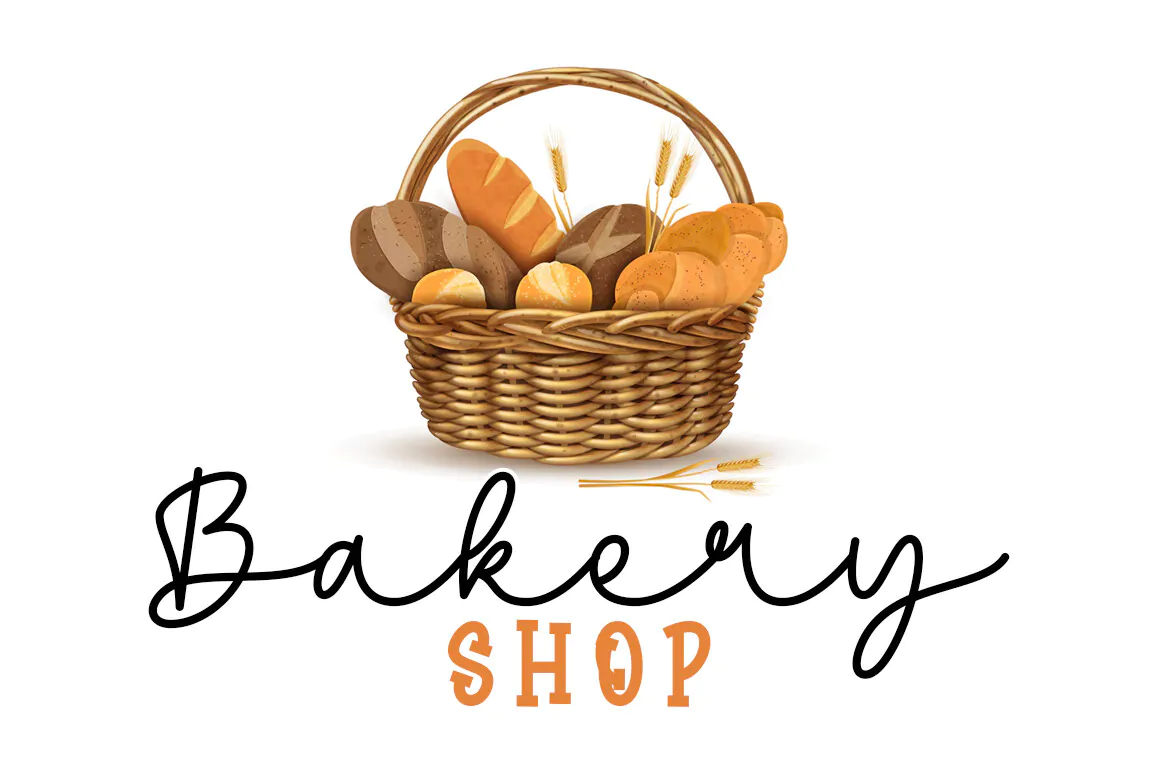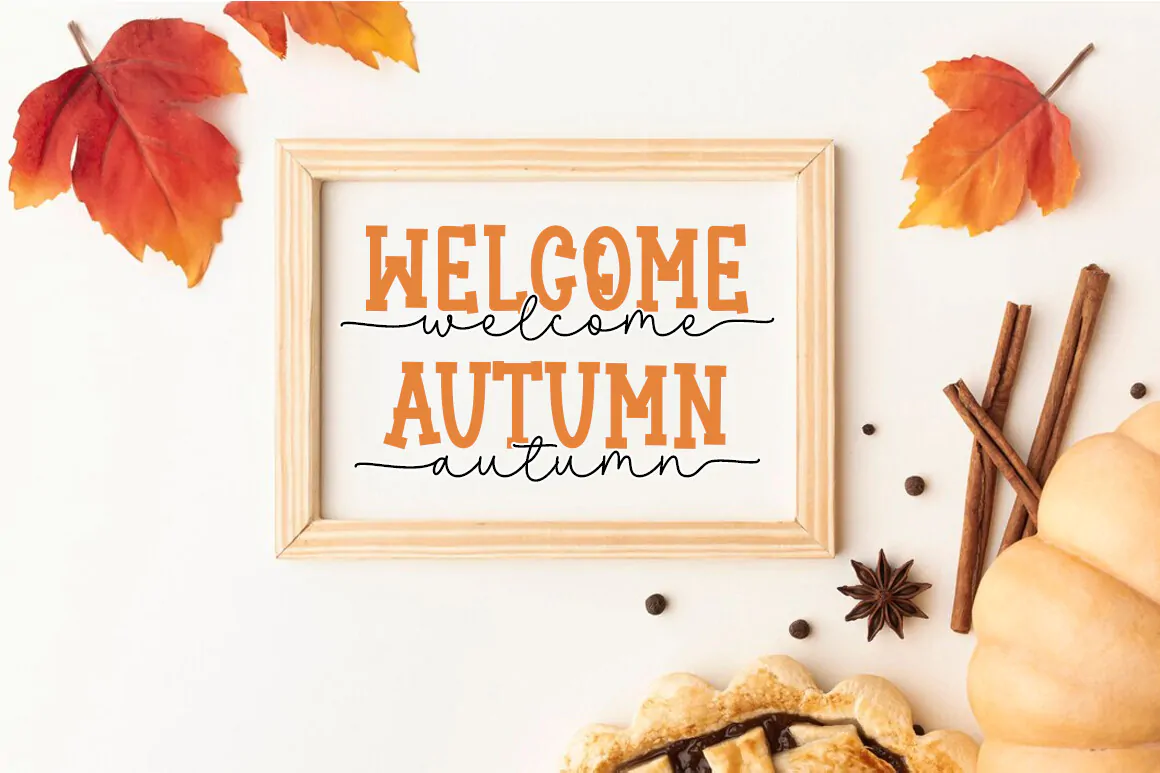
فونت دوتایی سرهم Sugar Honey
فونت دوتایی و سرهم
فونت دوتایی سرهم Sugar Honey مجموعهای از 2 قلم زیبای انگلیسی است که میتوانید در طرحهای مختلف همچون کارت ویزیت، کارت تبریک، بسته بندی محصولات و … از آن استفاده کنید.